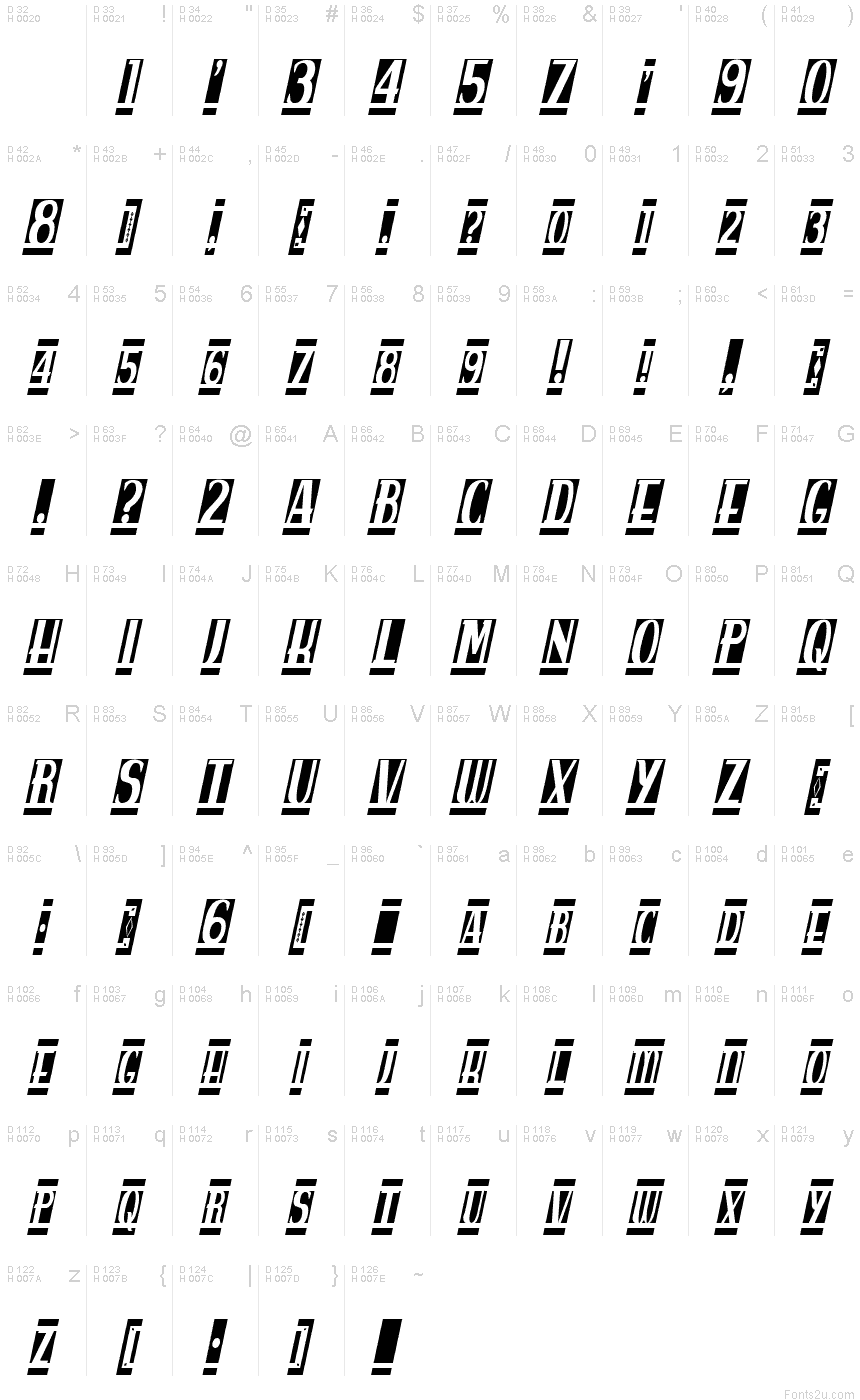
spankys bungalow blanco italico
Spanky's Bungalow Blanco Italico di Steven J. Lundeen è un font display retro gratuito, caratterizzato da un'inclinazione vivace e dall'atteggiamento deciso tipico delle scritte pubblicitarie di metà secolo. Le maiuscole risultano compatte e scenografiche, con tratti affusolati e angoli netti che conferiscono al carattere un ritmo rapido, tipico da poster, piuttosto che un aspetto liscio e levigato.
Si adatta perfettamente a brand ispirati ai diner, copertine di dischi, locandine di eventi, titoli e grandi headline, dove un font gratuito con così tanta personalità e contrasto può farsi notare. Usalo quando vuoi che parole brevi, monogrammi o iniziali abbiano un aspetto un po' sfacciato ed esuberante, perché le lettere portano già in sé lo spirito dei vecchi cartellonisti.